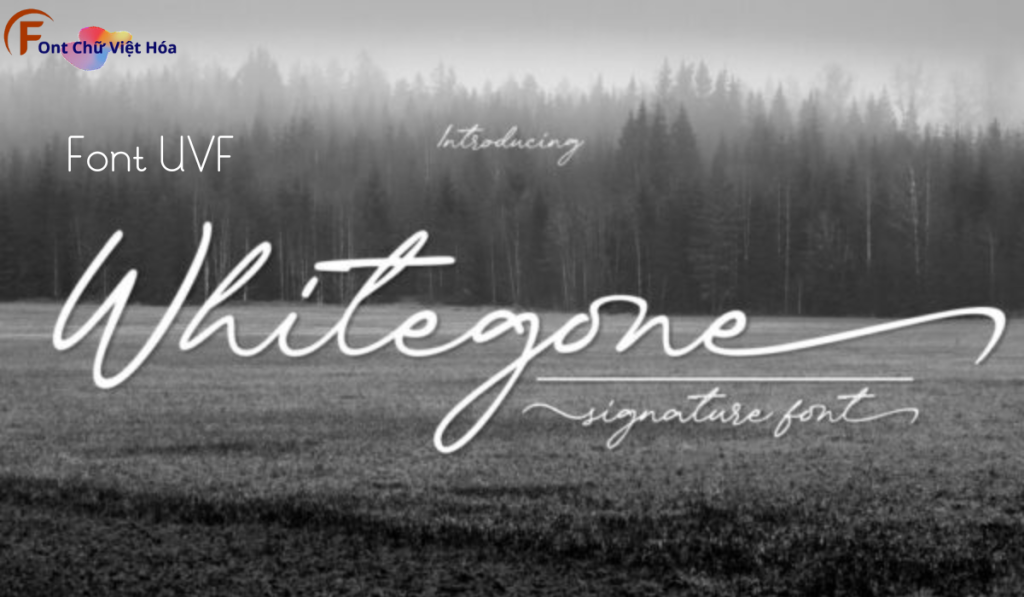
Font MJ Whitegone – Regular Việt Hóa
Font MJ Whitegone-Regular Việt Hóa
Tác giả: MJ
Bộ Font: MJ
Kiểu chữ: Sans-serif
Font MJ Whitegone-Regular Việt Hóa là một font chữ sans-serif cá tính, thuộc bộ font MJ. Được thiết kế với mục tiêu mang lại sự hiện đại và tinh tế, font này phù hợp cho các dự án thiết kế như poster, banner, và website. Với các nét chữ rõ ràng và độ dày đều đặn, Font MJ Whitegone-Regular Việt Hóa không chỉ dễ đọc mà còn tạo cảm giác chuyên nghiệp. Việc Việt hóa font giúp người dùng dễ dàng sử dụng trong các thiết kế tiếng Việt, mang lại sự tiện lợi và thẩm mỹ cao.